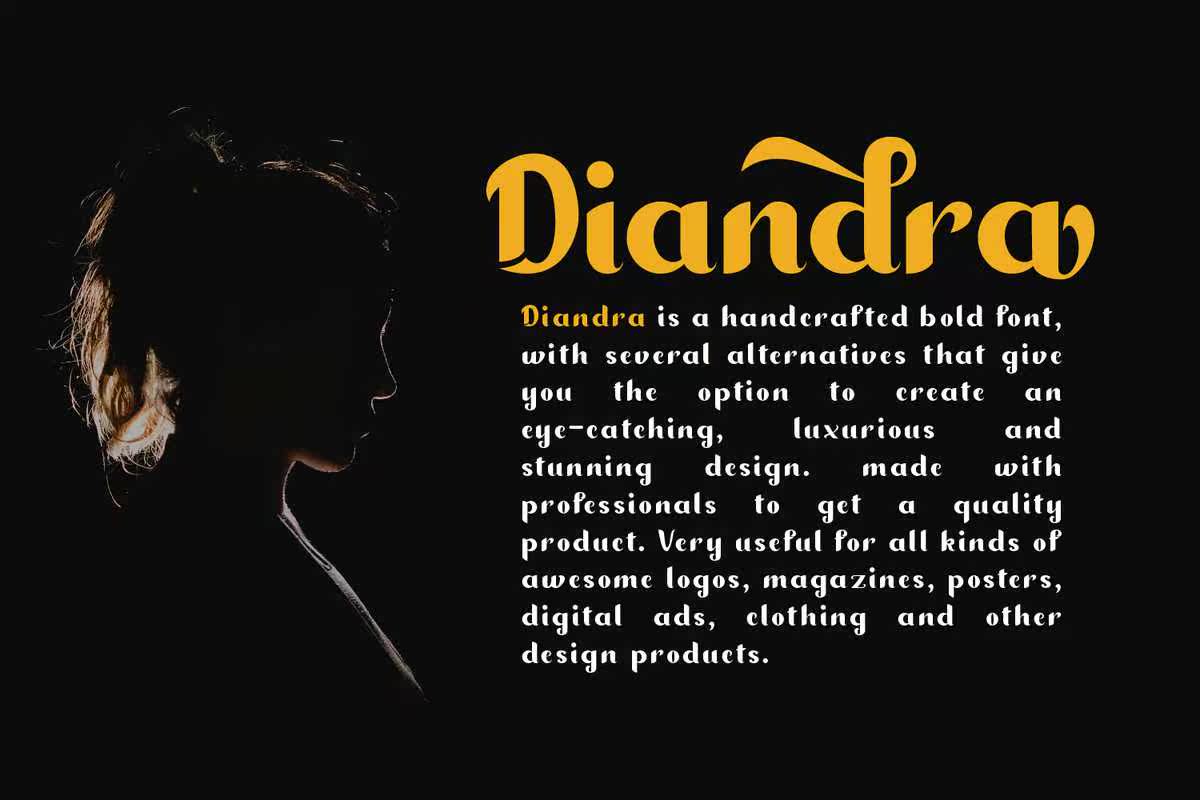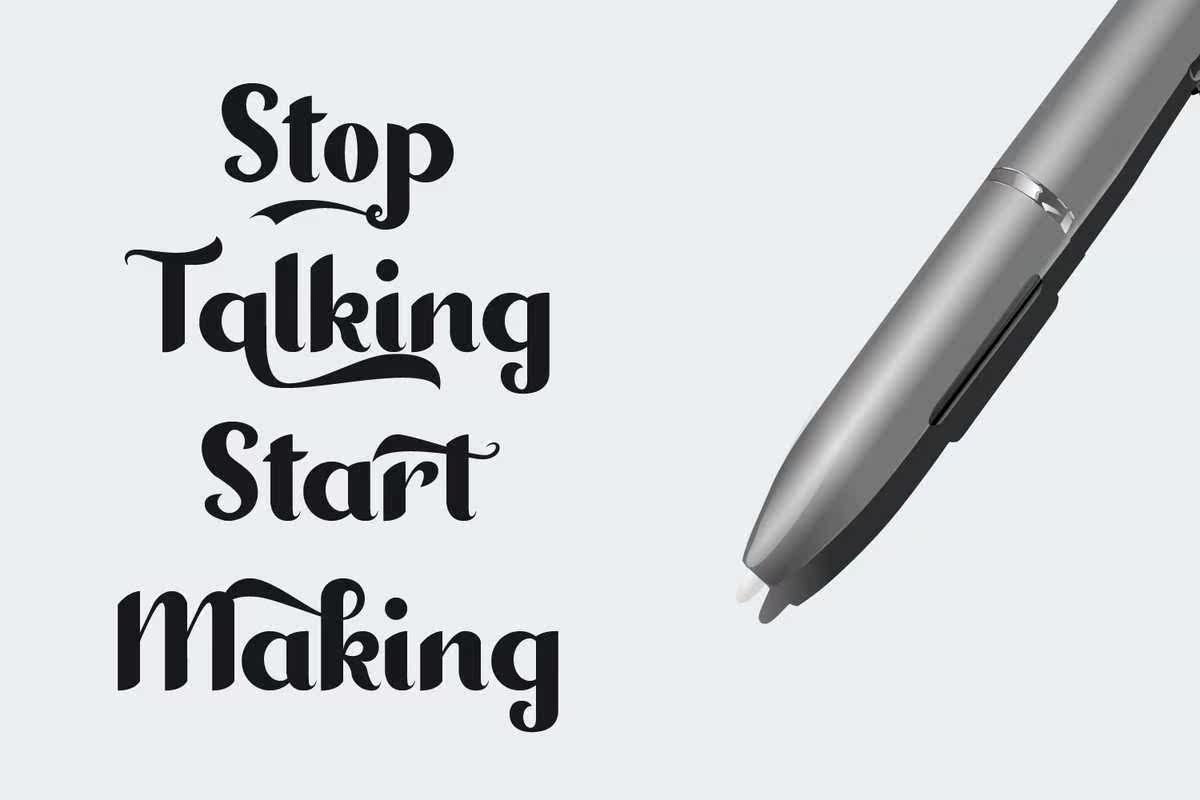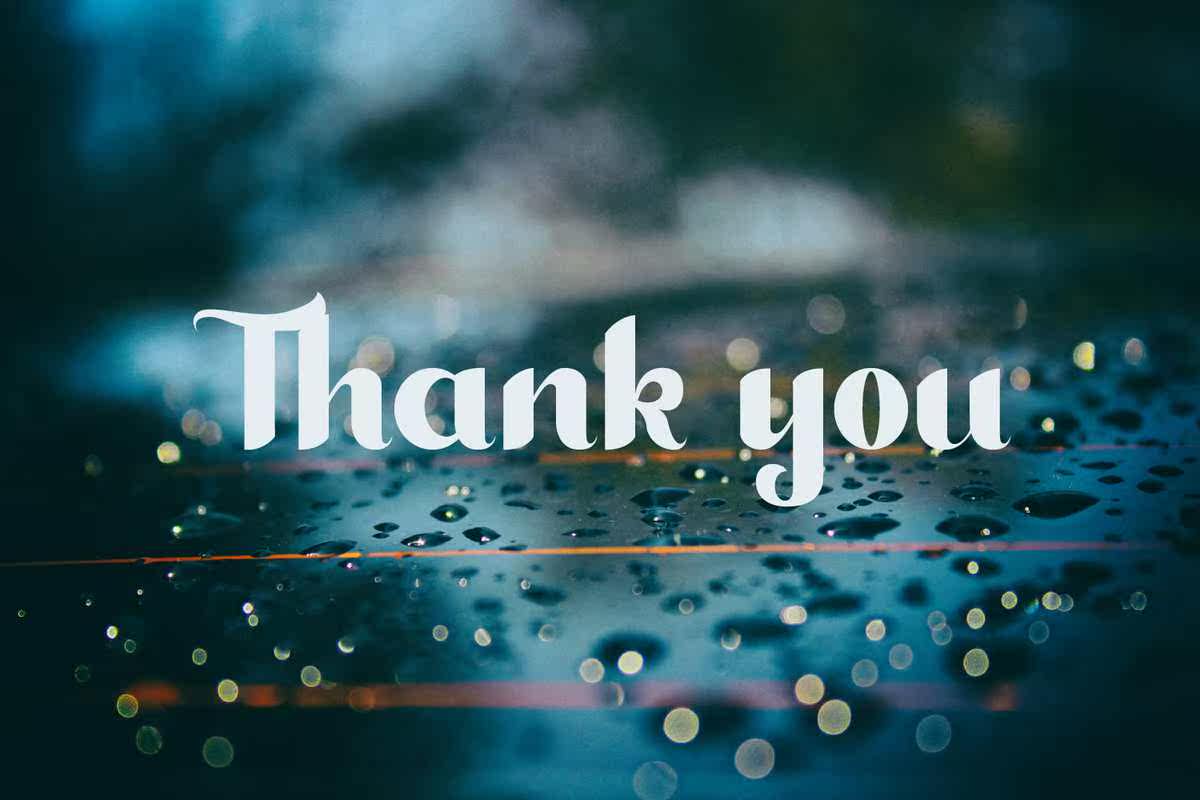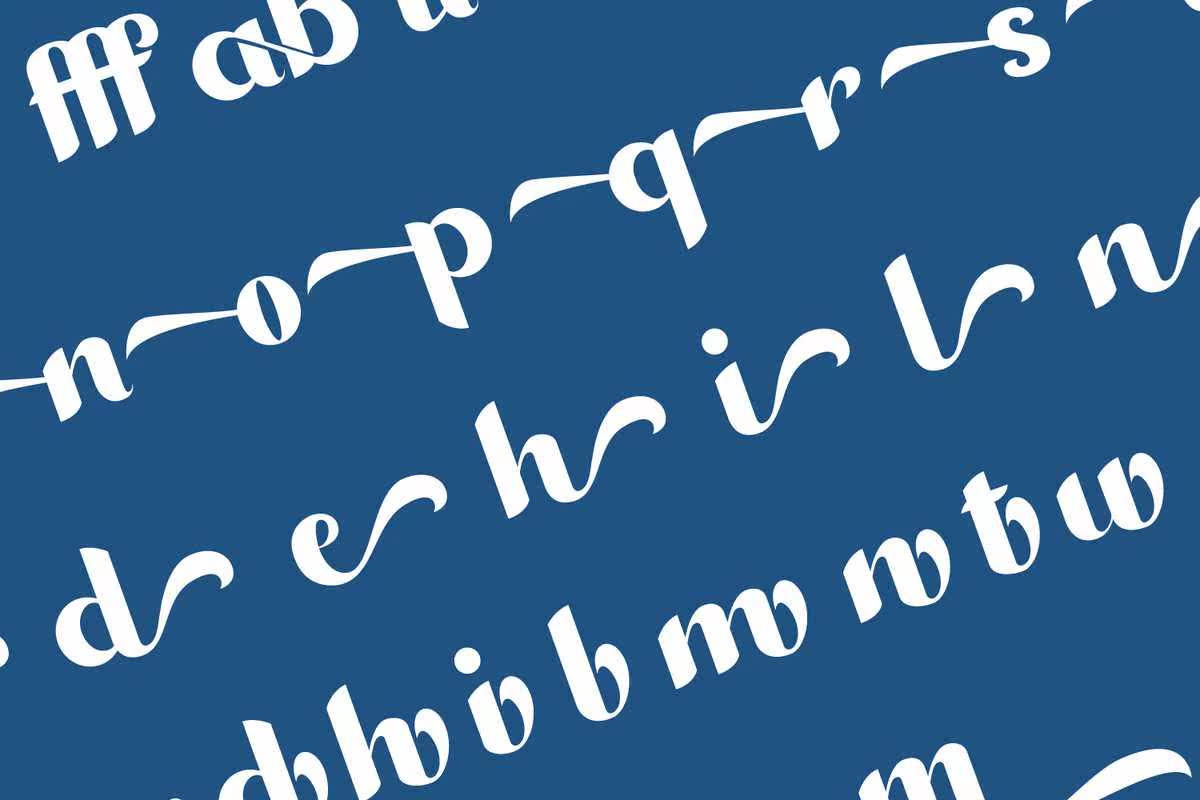
Diandra是手工制作的BoldFont,具有多种可选功能,让您可以选择创建一个吸引眼球、奢华和惊艳的设计。让专业人士获得Aquality产品。非常适用于各种令人敬畏的徽标、杂志、海报、数字广告、服装和其他设计产品。Diandra是手工制作的BoldFont,通过各种可选的设计,让您可以选择创造一个吸引眼球的、奢华的、令人惊叹的设计。让专业人士获得Aquality产品。非常适合各种令人敬畏的徽标、杂志、海报、数字广告、服装和其他设计产品。